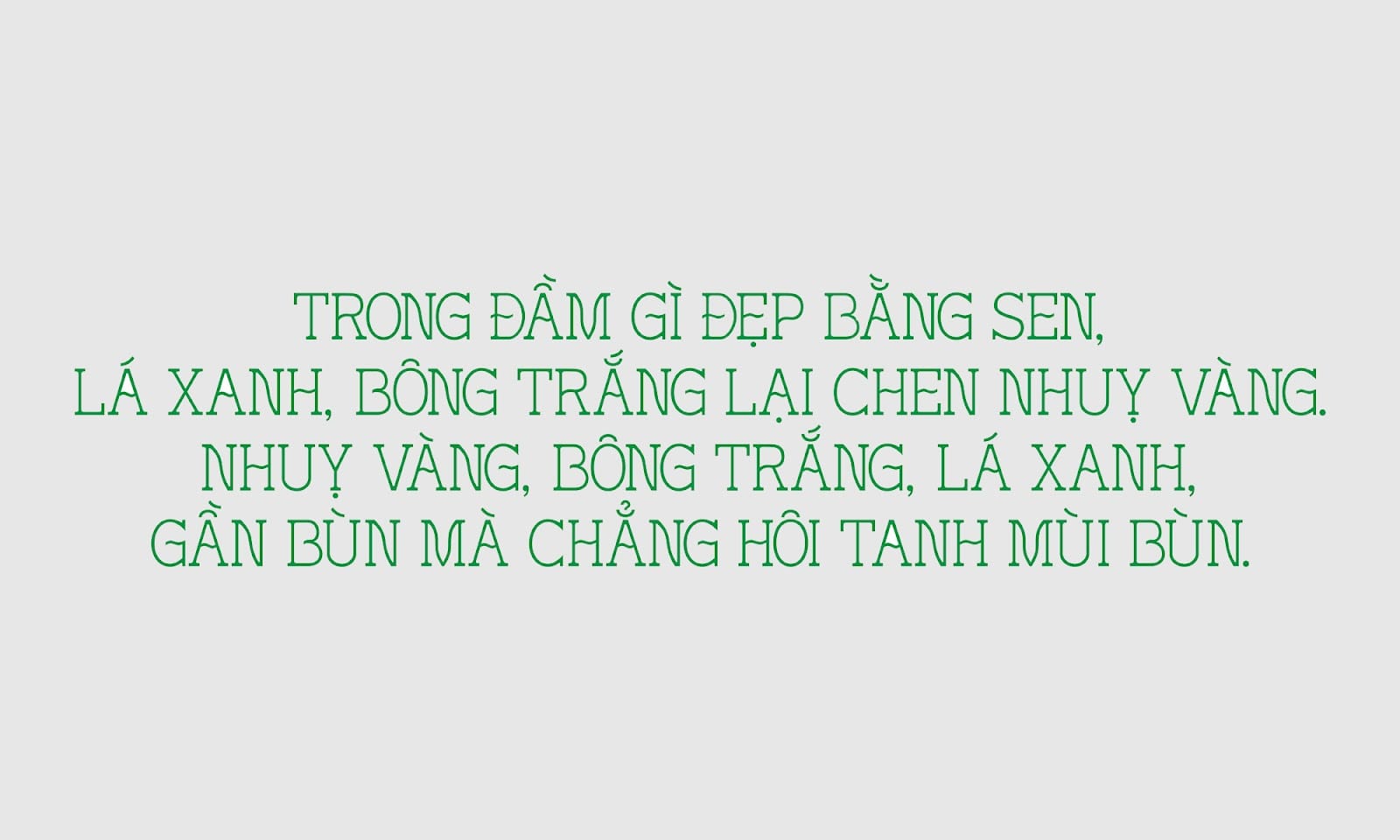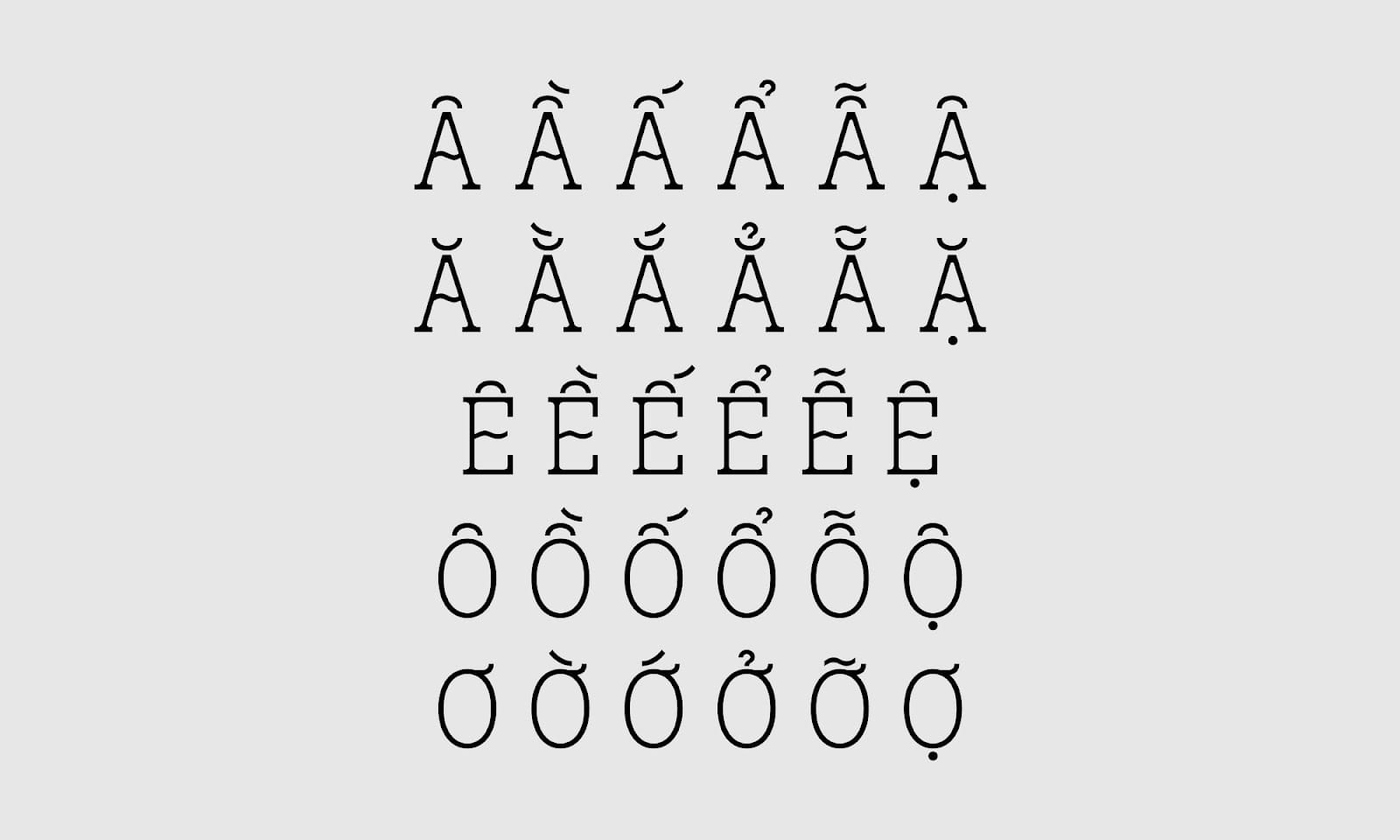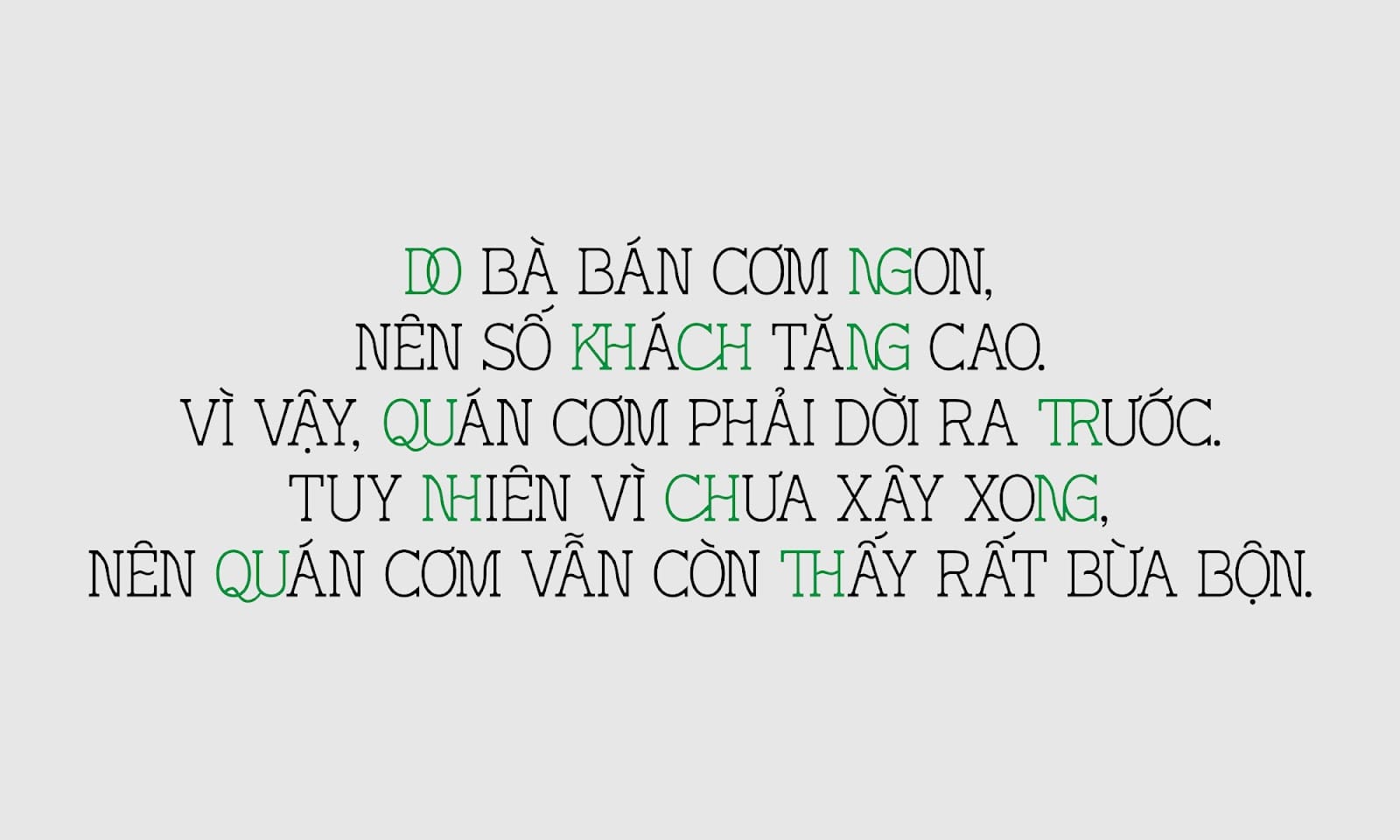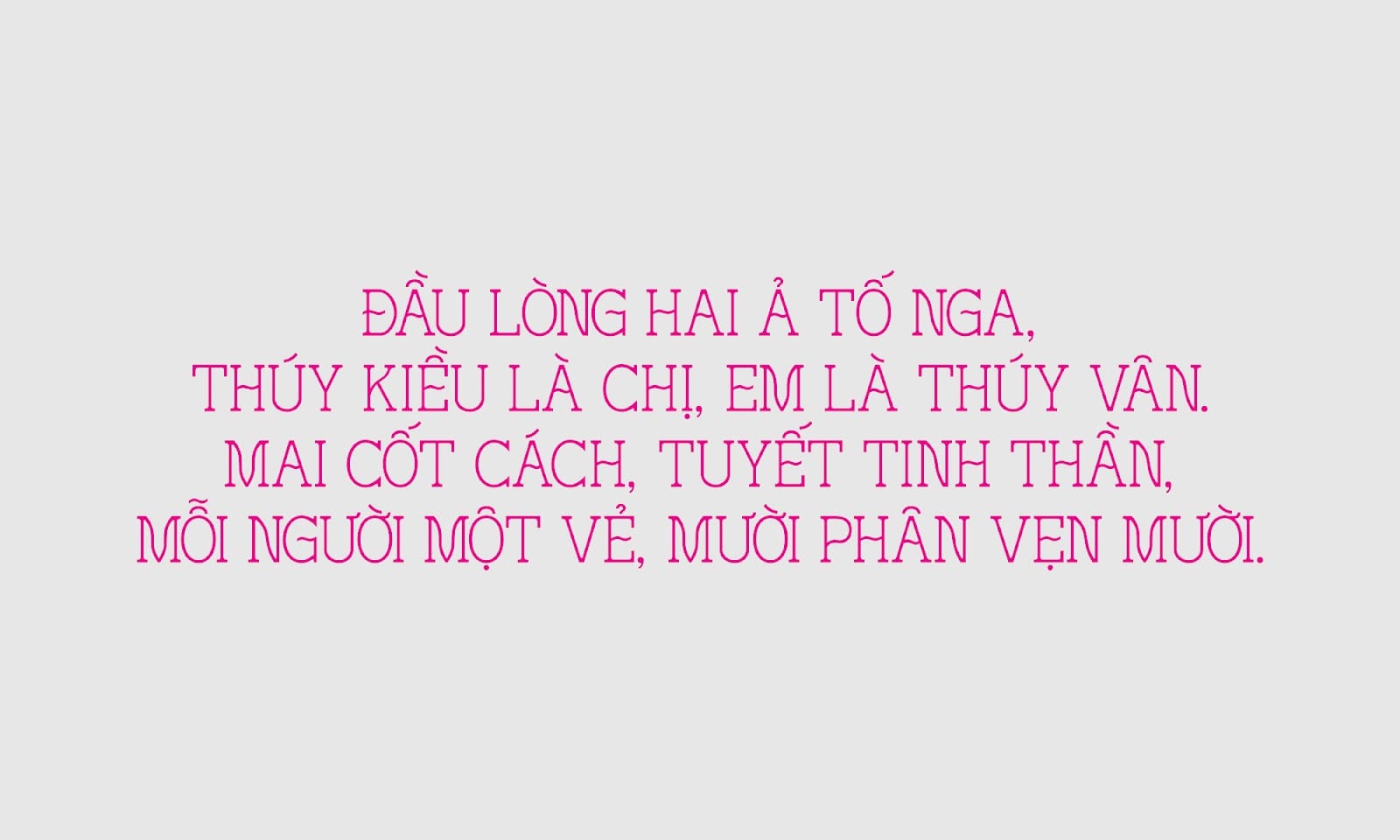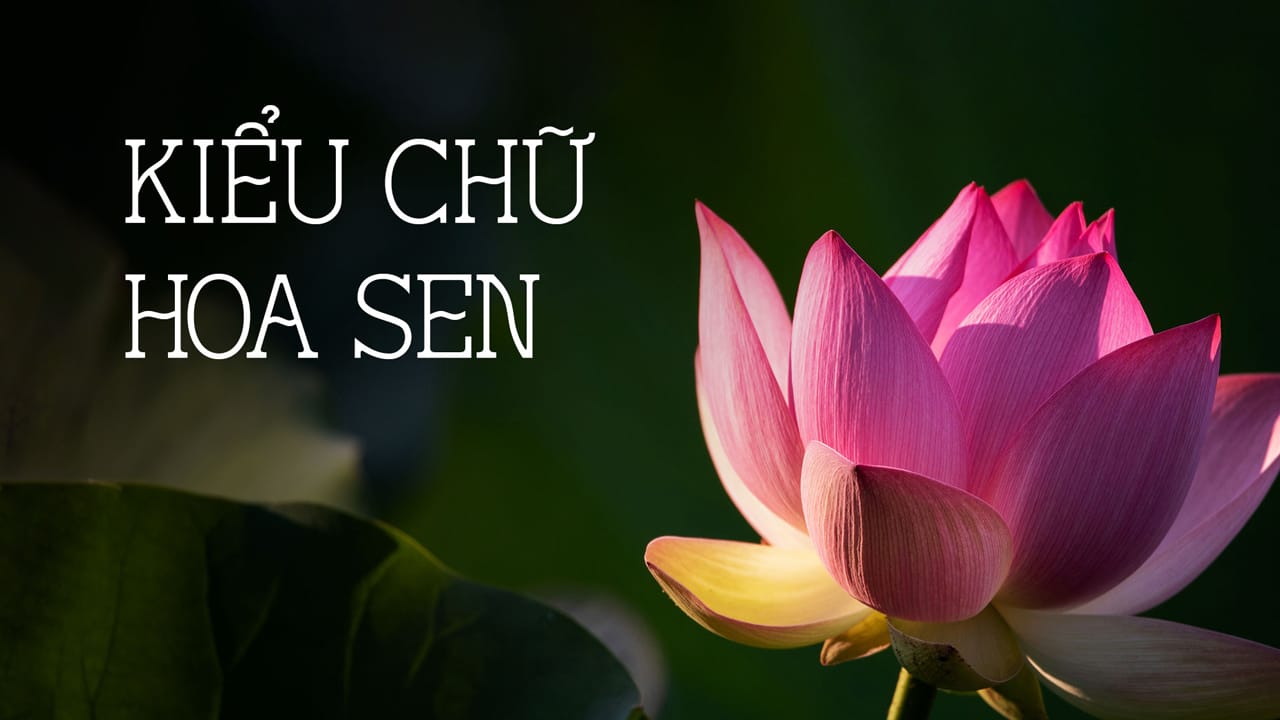
Hoa sen là một trong những loài hoa mang vẻ đẹp nhẹ nhàng, và nhiều ý nghĩa sâu sắc trong văn hóa của Việt Nam. Hoa sen nổi bật vươn lên và phát triển giữa bùn lầy, với những cánh hoa xinh đẹp làm say mê những ánh nhìn. Với nét đẹp và môi trường sống ấy, hoa sen tượng trưng cho sự thuần khiết cùng nghị lực phi thường.
Hoa Sen Typeface cũng được lấy ý tưởng từ sự mềm mại của Hoa Sen. Với thân sen thon và dài uốn lượn một cách tự nhiên, cùng những đường cong mượt mà từ cánh hoa. Sẽ là sự kết hợp hoàn hảo để tạo nên kiểu chữ. Font được thiết kế bởi Trương Nguyên Huy và chia sẻ miễn phí cho mục đích cá nhân và thương mại.